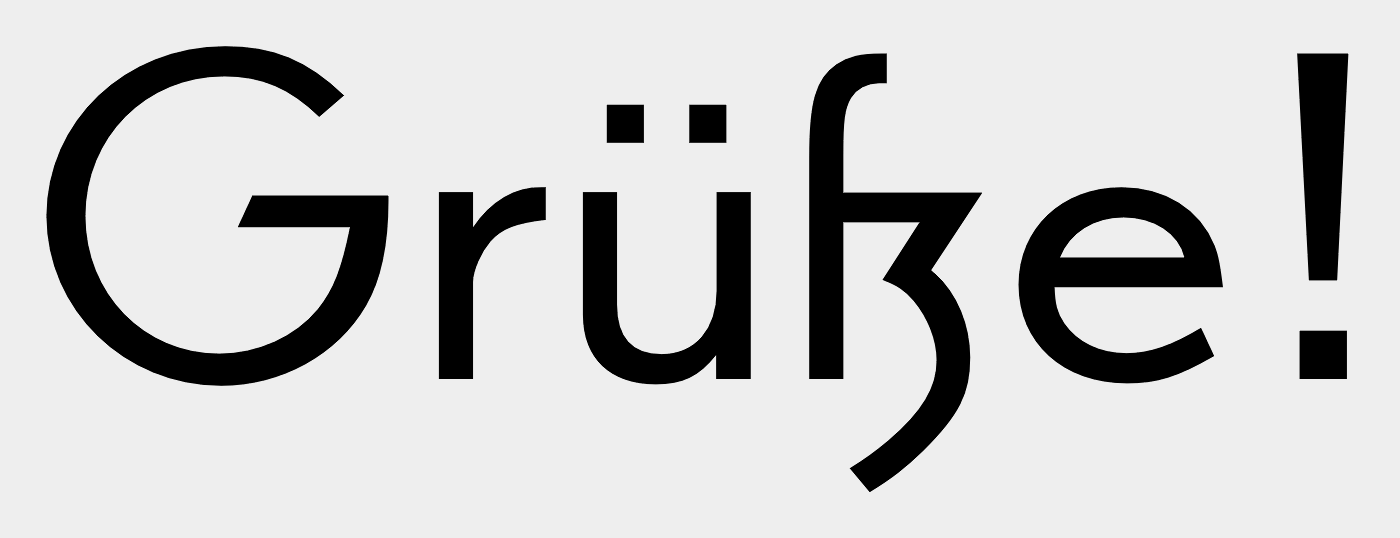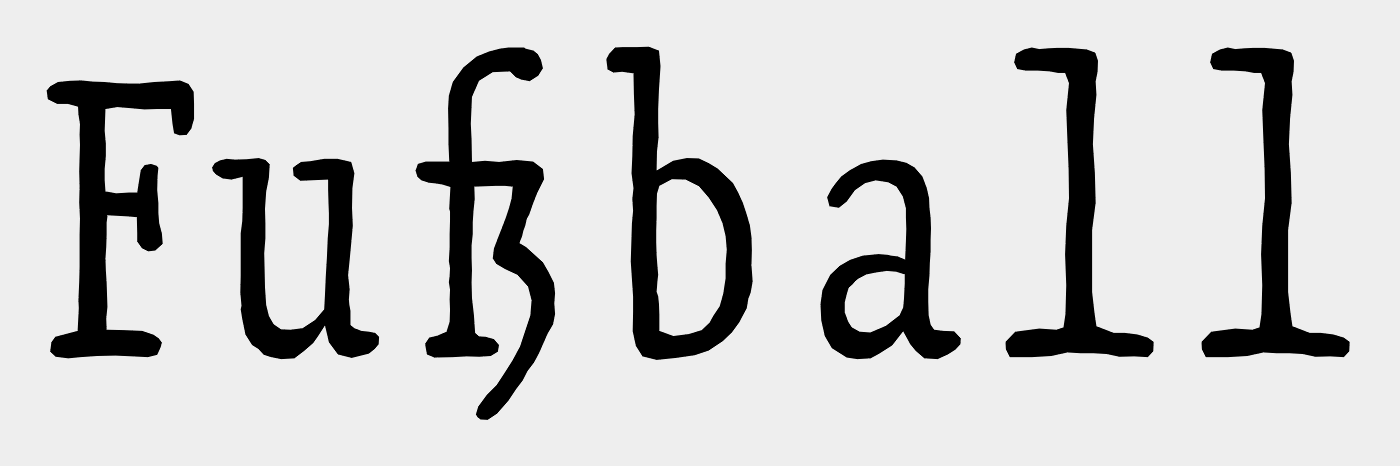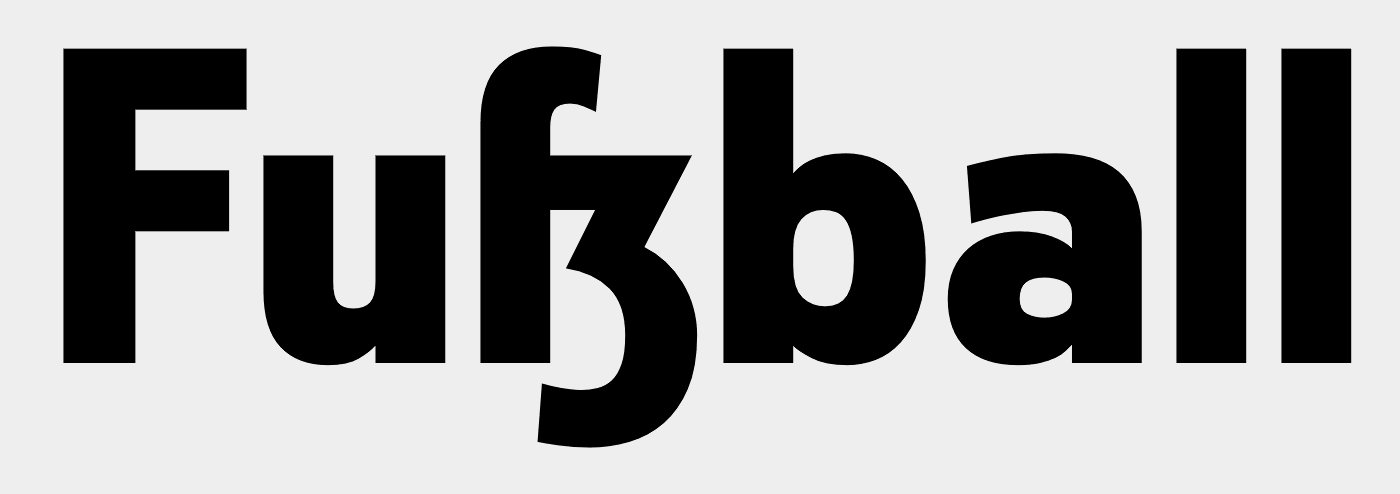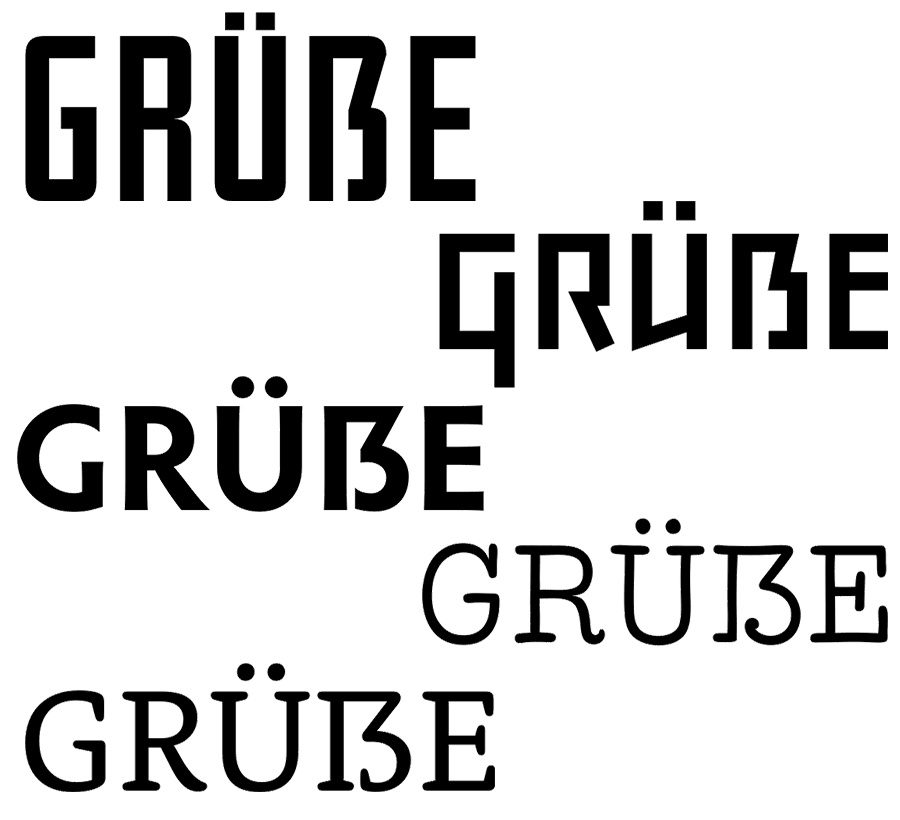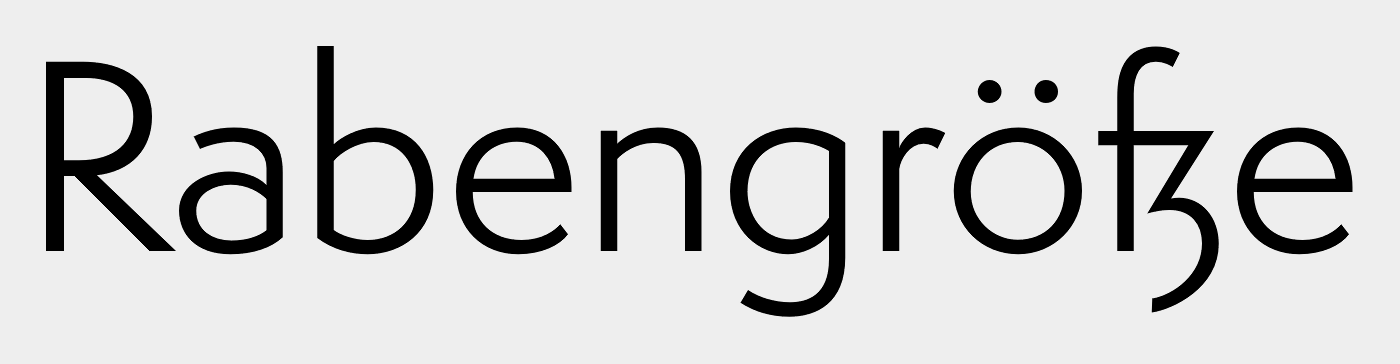
typen mit sz-ligatur
liebe gemeinschaft,
diesmal bin ich auf der suche nach schrifttypen die eine ganz und gar wunderbare sz-ligatur im zeichensatz (anstellen des ß) aufweisen. im anhand als frisch geschlüpftes beispiel die euclid.
Eigenwerbung Canapé (als Alternativform zum normalen ß)
(tut nichts zur Sache, aber das lange s im ersten Wort ist da fälschlicherweise nicht die Swash-Variante sondern die manuell gesetzte normale Kursivvariante)
Ich mag diese ſ-z Abart des ß sehr gern. Gibt davon auch Versal-ß Varianten? Im Veral-ß Thread ist mir diese Form noch nicht begegnet.
Gut, das ist ja mehr ein S-Z. Vielleicht muss das Versal-ſ doch reanimiert werden ;-)
re-animiert? ein Versal ſ hat es, mangels Notwendigkeit nie gegeben. Zudem müsste man dazu dann auch noch eine Einsatzregel erfinden. Da Worte ja mit dem "runden" S beginnen, müsste die ja dann umgekehrt, als die s/ſ Regel lauten:
Г ist eine 2 Form des S, entsprechend dem ſ zum s.
S ist das Anfangs-S, es steht auch nach einer Wortfuge, sonst wird im Versalsatz das Versal-Lang-S (Г) verwendet.
Und dann könnte man das Versal-ß aus einer Ligatur aus Г und S herleiten, bzw aus Г und Ʒ
re-animiert? ein Versal ſ hat es, mangels Notwendigkeit nie gegeben.
Also »nie« stimmt nicht ganz. http://www.typografie.info/3/page/artikel.htm/_/wissen/ehmcke-antiqua
Und »Notwendigkeit« ist relativ. Wenn man ſ als Morphemgrenzen-Kennzeichner für sinnvoll erachtet und es Versal-Satz (zumindest in Antiqua) gibt, dann wäre auch ein großes ſ als sinnvoll zu betrachten.
Nun ja, hier bin ich ja den umgekehrten Weg gegangen, um so ein "Langs-S" zu erfinden, und bin eben so zum Г gekommen.
Ich weiß, eigentlich ein kyrillisches G, aber wenn die unser H als N C als S und P als R missbrauchen  :baeh:  , warum wir das Г dann nicht als lang-S?
Wunderte mich übrigens auch über die Formulierung »sz-Ligatur statt ß«. Die Ausgestaltung der Glyphe ändert ja nichts daran, dass das Zeichen weiterhin ein ß ist.
Dabei haben wir doch erst kürzlich im Diskussionsfaden zum okkulten (Nicht-)Bindegedöns festgestellt, dass wir fein unterscheiden müssen zwischen ß als eigenständigem Buchstaben in der deutschen Orthographie, einer ſz-Ligatur für Nachtſzene und einer ſs-Ligatur für Wörter wie muſs in neuer Rechtschreibung, wobei wegen letzterer das ß sich ja auch eher am ſz orientieren sollte ...
Aber in der Tat: Wer ein Versal-ß für den Versalsatz als nötig erachtet, ist vom Versal-ſ nur noch einen kleinen Schritt entfernt ... ;-)
... allen komischen Biermarken wie Fürs-
tenberg oder seit neuestem auch Wars-
feiner zum Trotze ... ;-)
Dabei haben wir doch erst kürzlich im Diskussionsfaden zum okkulten (Nicht-)Bindegedöns festgestellt, dass wir fein unterscheiden müssen zwischen ß als eigenständigem Buchstaben in der deutschen Orthographie, einer ſz-Ligatur für Nachtſzene und einer ſs-Ligatur für Wörter wie muſs in neuer Rechtschreibung, wobei wegen letzterer das ß sich ja auch eher am ſz orientieren sollte ...
Heyse hat für seine Grammatik mit der heute benutzten S-Schreibung eine solche ſs-Ligatur fertigen lassen:
Was heißt »könnte«, das tut man ja bereits …
Oder so: https://www.myfonts.com/fonts/fontfont/videtur/pro-regular/?meta=/240901/FUẞSOHLE/FF+Videtur+Pro+Regular
Edit: Ist das tatsächlich schon alles, was sich an Beispielen für die Gemeinen finden lässt?! Ich habe da irgendwie mehr erwartet, aber bisher auch nichts weiter finden können …  :-? Die kann man auch nicht so einfach über die Myfonts-Suche rausfischen wie beim Versaleszett, oder?
Bei den Versalvarianten, die Ralf eingestellt hat, habe ich bei den unteren beiden spontan »Grütze« gelesen. Huch! :-?